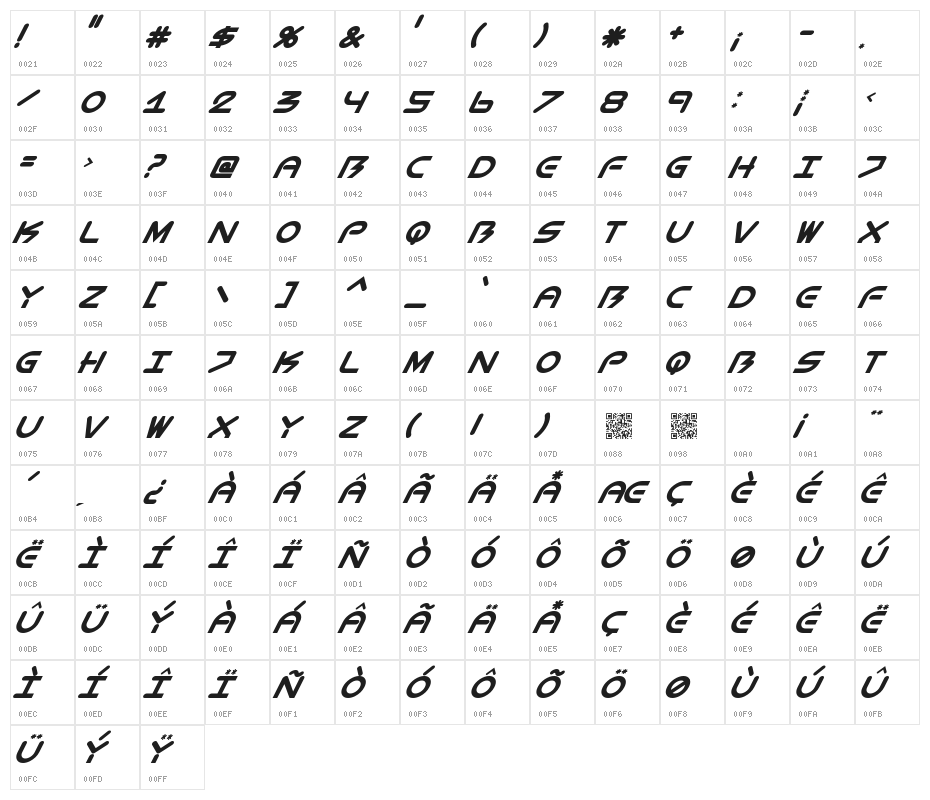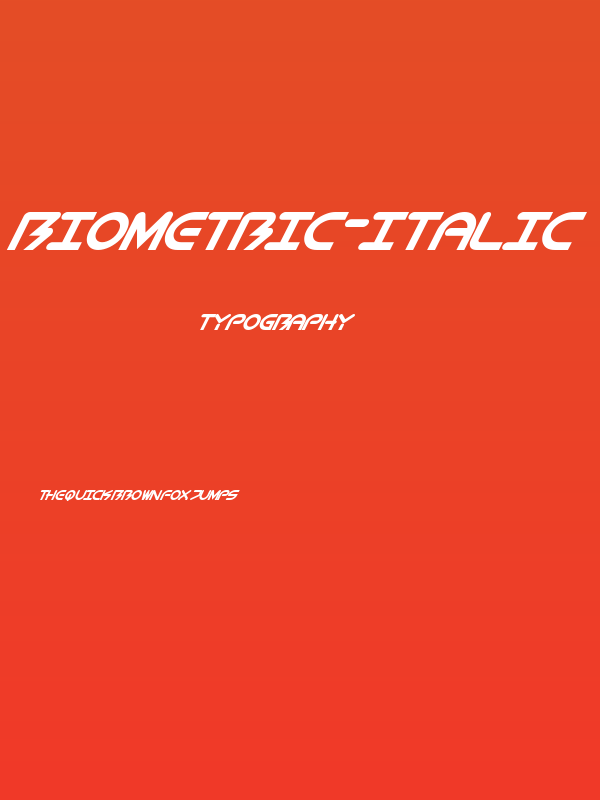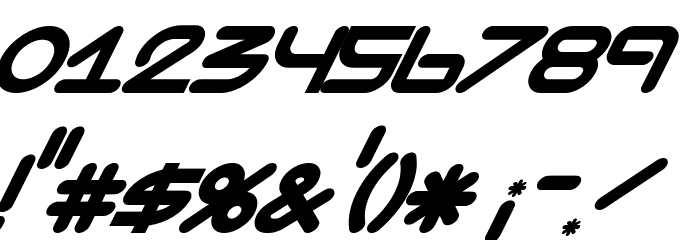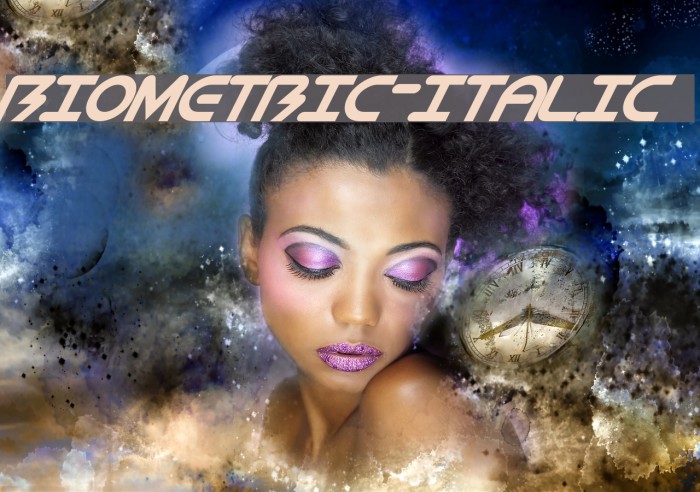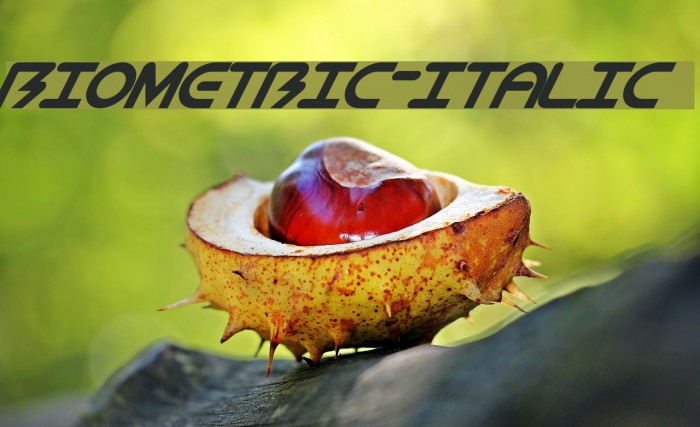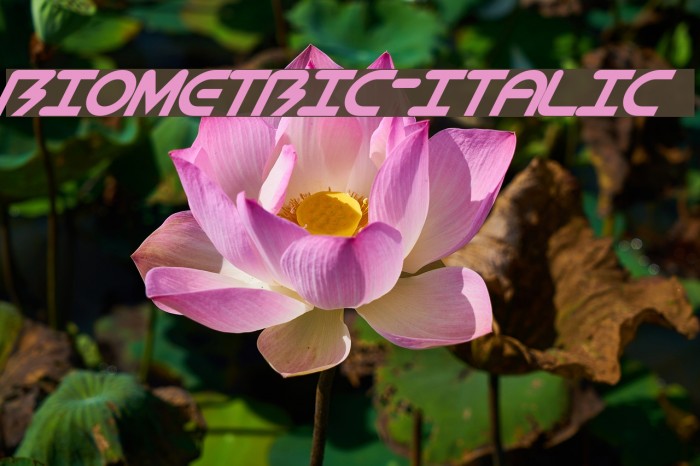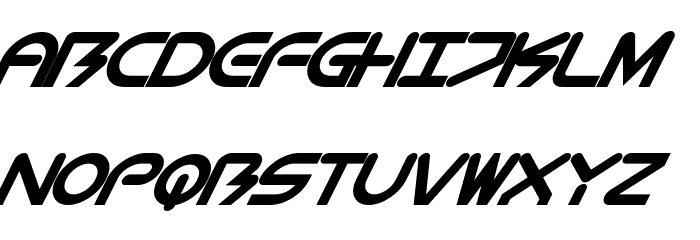
BioMetric-Italic Font
| النمط العام | Futuristic, Dynamic |
| حالة الاستخدام | Logos, Headlines, Advertising |
| مشاريع مقترحة | Ideal for technology branding, sports team logos, dynamic advertising, and futuristic designs. |